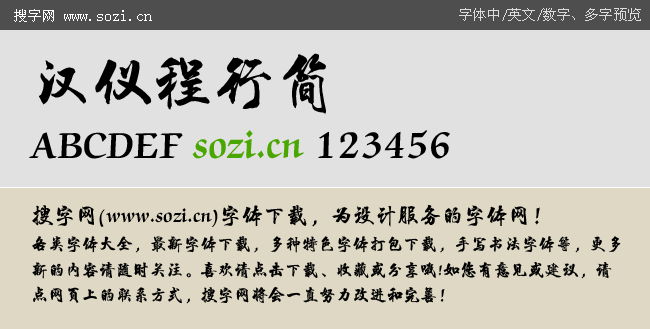
漢儀程行簡(jiǎn)
感謝漢儀公司開(kāi)發(fā)的這款漂亮的字體,這是一款柔軟飽滿書(shū)法字體,歡迎下載。 本字體由熱心網(wǎng)友免費(fèi)分享,僅限于個(gè)人收藏學(xué)習(xí),如需要商用,敬請(qǐng)聯(lián)系漢儀官方。
• 風(fēng)格類別: 行楷